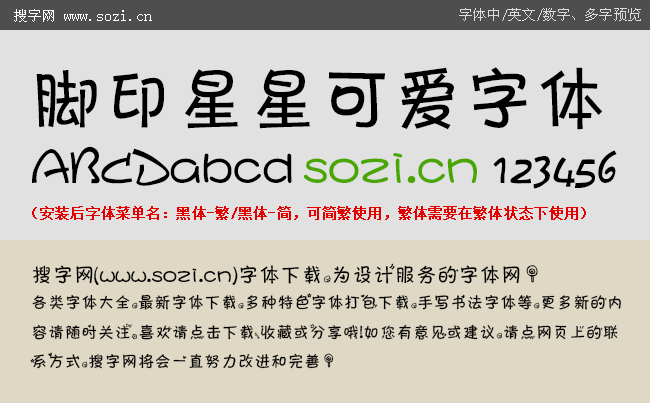
腳印星星可愛字體
搜字網(wǎng)給大家提供一款腳印星星可愛字體手機(jī)中文字體下載。這款手機(jī)中文字體以POP字體為原形,在保留字體風(fēng)格的同時(shí),將標(biāo)點(diǎn)都改成了有趣的卡通圖形,是一款很有趣的卡通字體,非常適合喜歡卡通的朋友在手機(jī)上安裝使用。